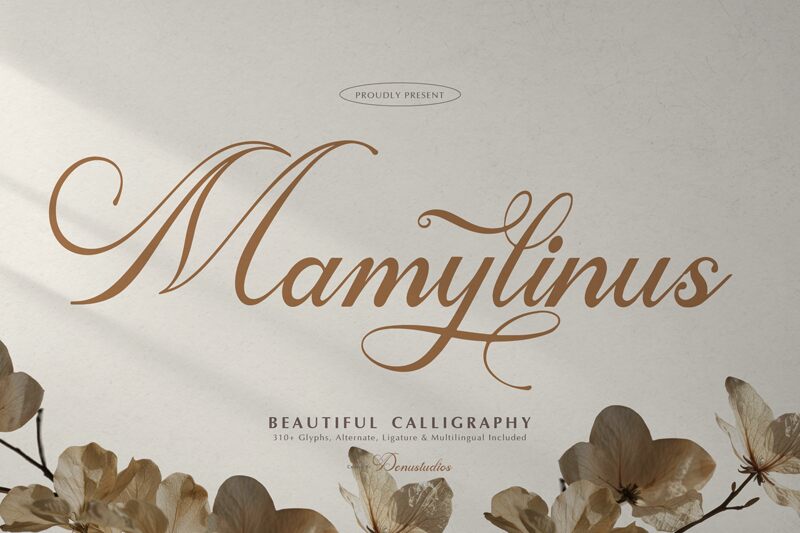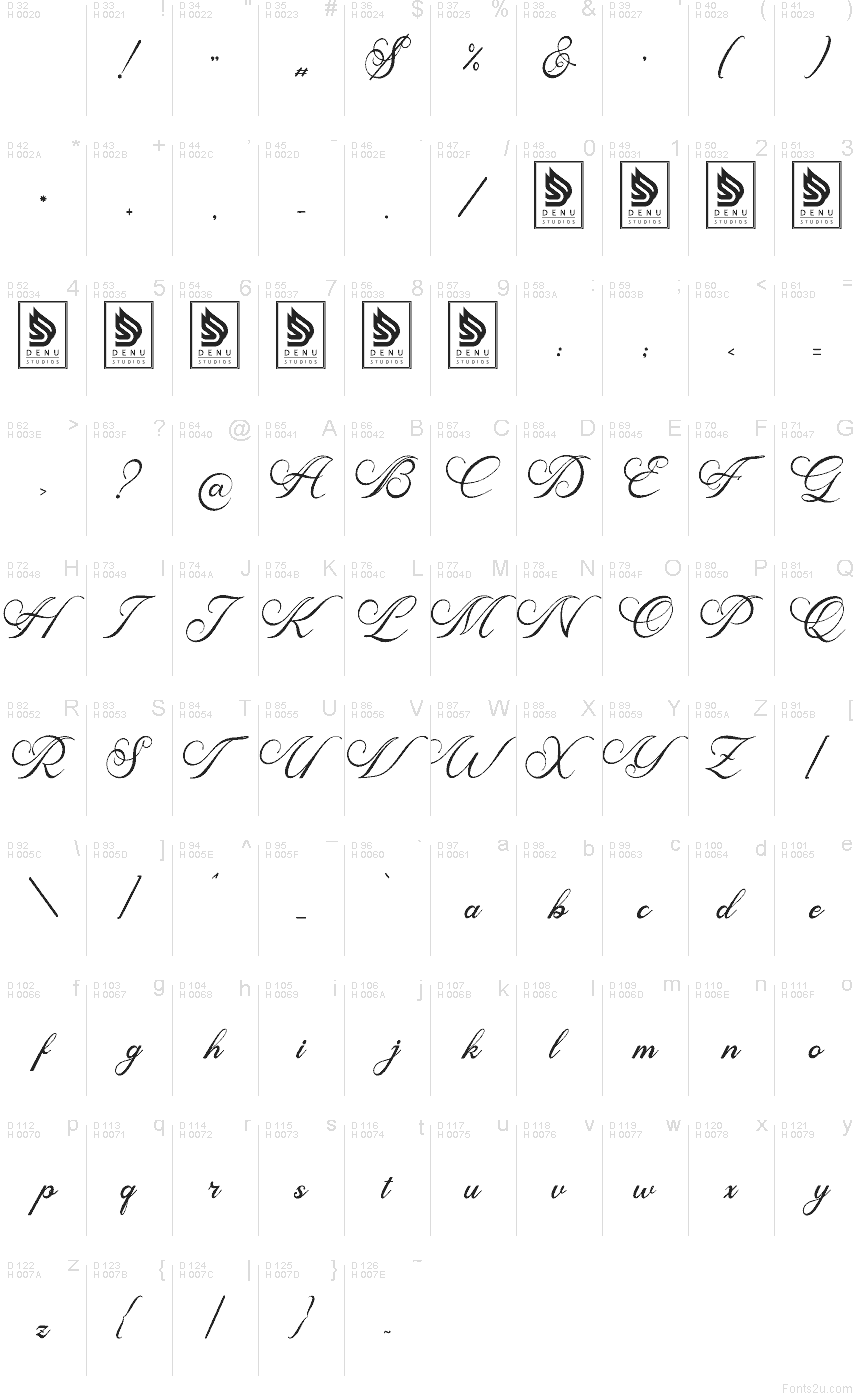
Mamylinus de Denustudios es una tipografía caligráfica gratuita con un aire romántico y de alto contraste. Sus letras combinan trazos de entrada largos y fluidos con curvas finas y delicadas, logrando que las palabras se sientan aireadas y teatrales en lugar de formales, con florituras que regresan constantemente al ritmo del diseño.
Se adapta perfectamente al branding, papelería de bodas, packaging de belleza, señalética de boutiques y portadas de revistas, donde el dinamismo de sus trazos ayuda a resaltar el diseño. Como fuente gratuita, también es ideal para tarjetas de título, invitaciones y encabezados cortos, ya que sus extensiones y descendentes en bucle otorgan una sensación de ocasión especial incluso a las palabras más breves.